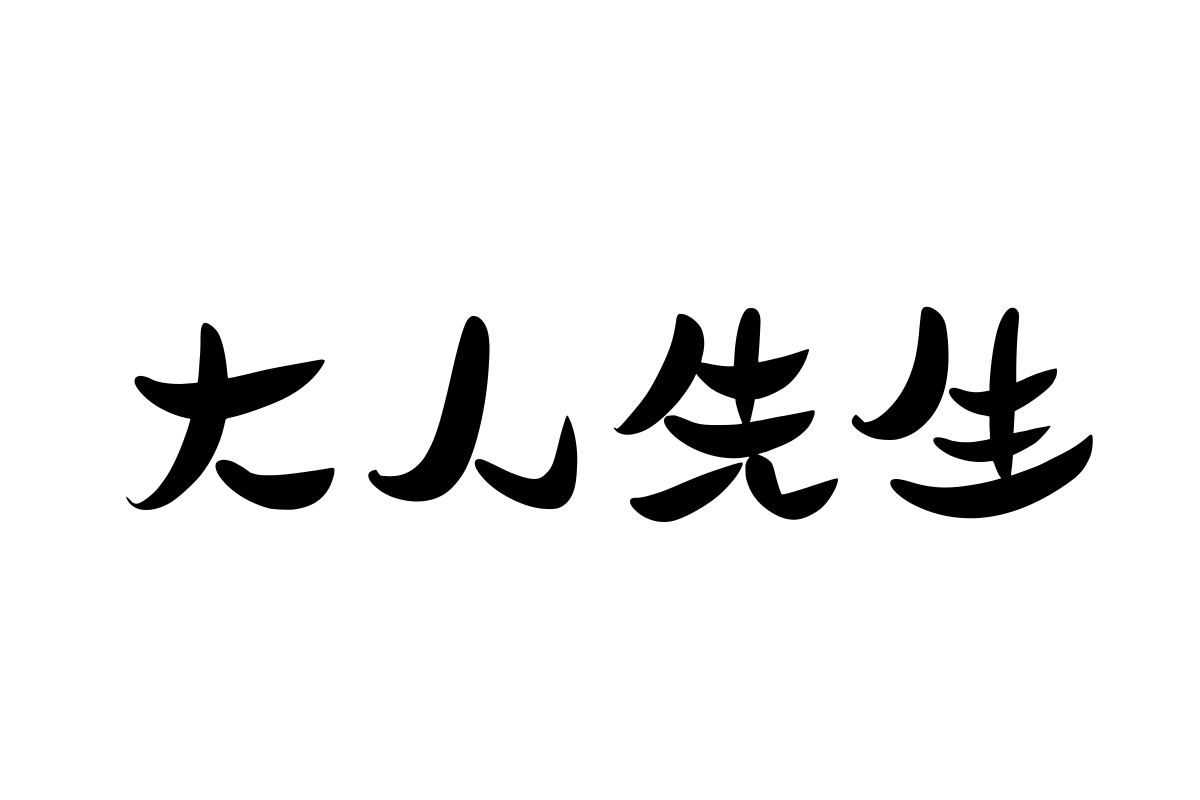
三极追风体是一种具有独特风格和特色的中文字体,它由设计师张海峰于2013年设计。这种字体以其独特的笔画结构和流畅的线条而受到许多设计师的喜爱。
三极追风体的笔画粗细变化较大,既有粗犷的线条,又有细腻的笔触,这使得它在视觉上呈现出一种独特的美感。同时,它的笔画结构也较为复杂,需要一定的练习才能熟练掌握。
此外,三极追风体还具有一定的装饰性,例如在字形中加入一些装饰元素,使得整个字体更加生动有趣。这使得它在广告、标志等领域得到了广泛的应用。
总的来说,三极追风体是一种非常有个性和创意的中文字体,它不仅能够为设计作品增添独特的视觉效果,还能够表达出设计师的个性和情感。